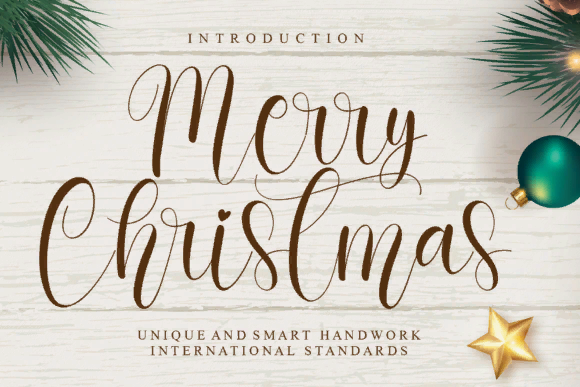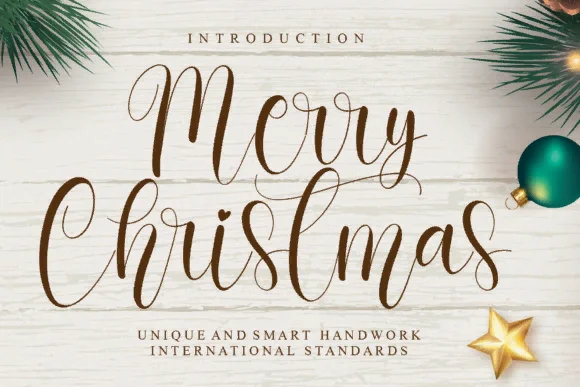
Название: Merry Christmas Font (2021)
Merry Christmas - шикарный, изысканный шрифт, излучающий утонченность и элегантность.
Стильные чередования и лигатуры делают этот шрифт идеальным для любого проекта.